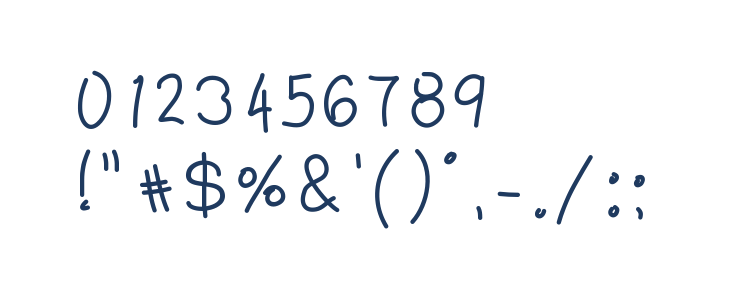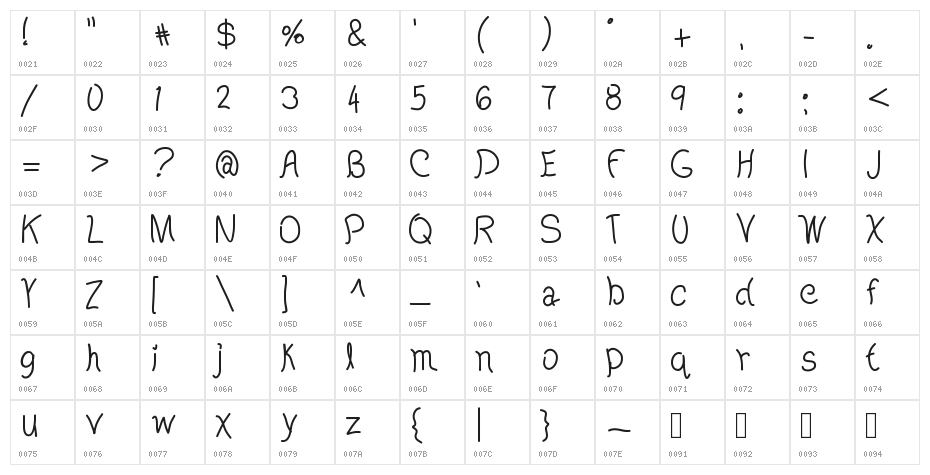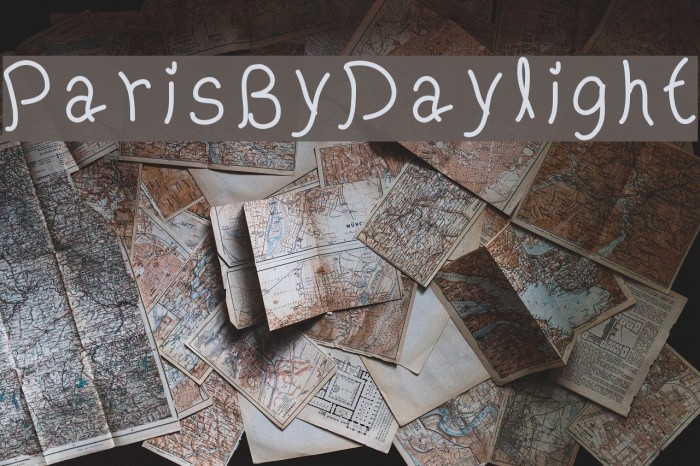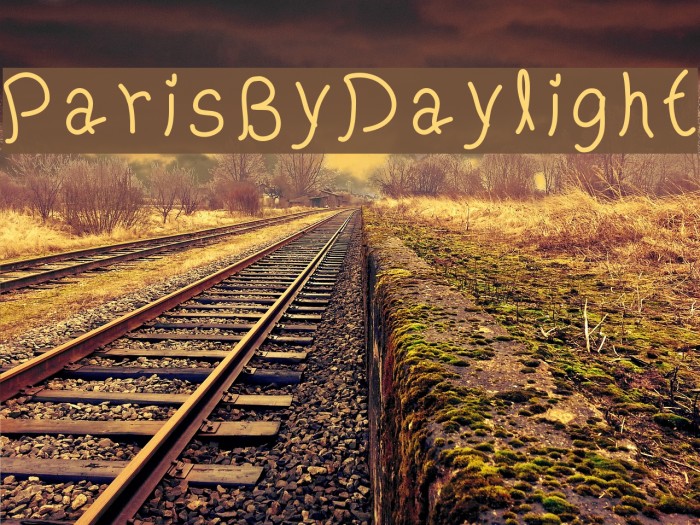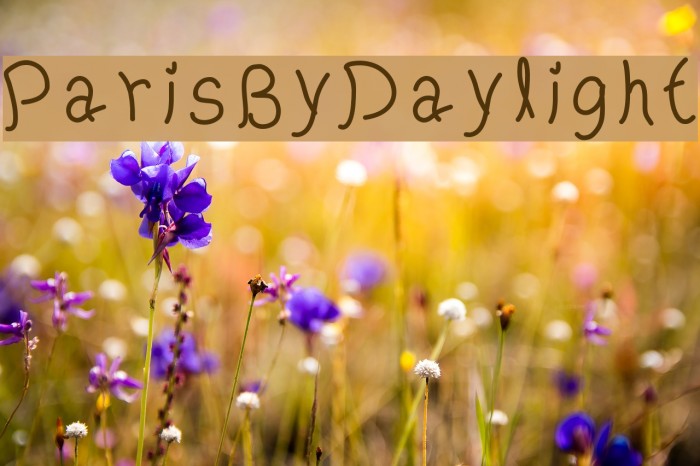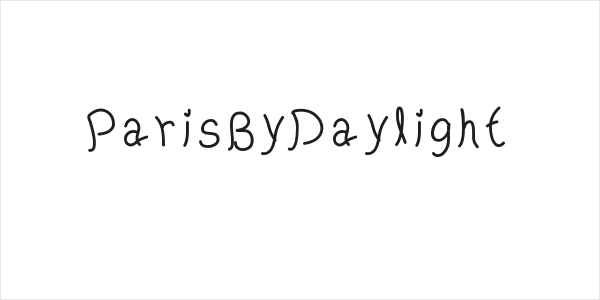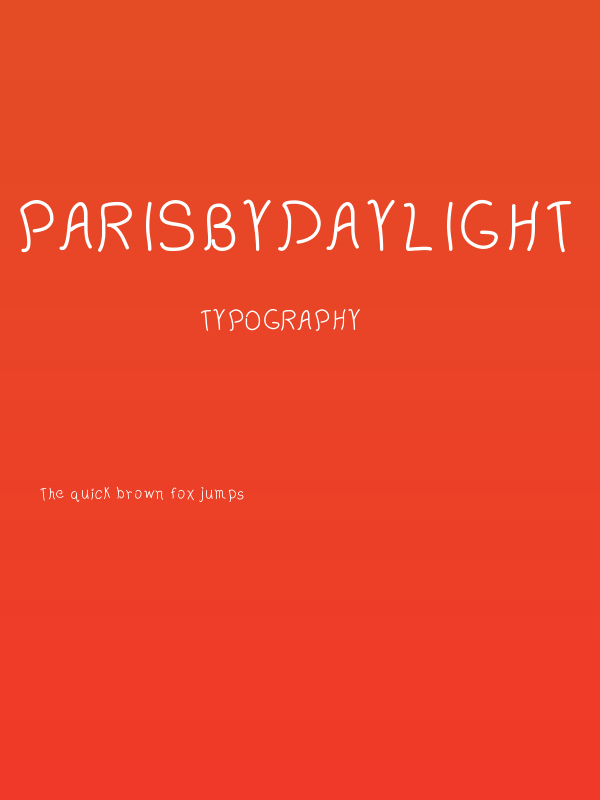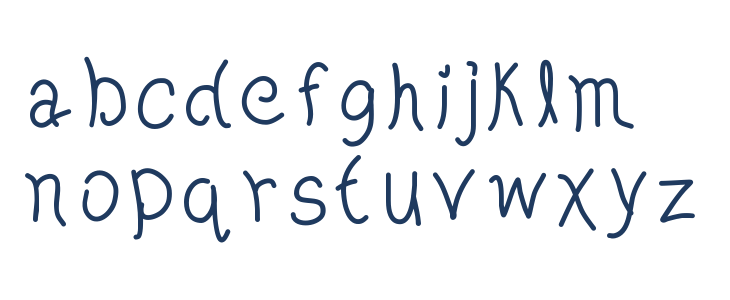
ParisByDaylight Font
| النمط العام | Playful, Whimsical |
| حالة الاستخدام | Headlines, Logos, Creative projects |
| مشاريع مقترحة | Ideal for children's books, greeting cards, playful branding, and creative posters. |